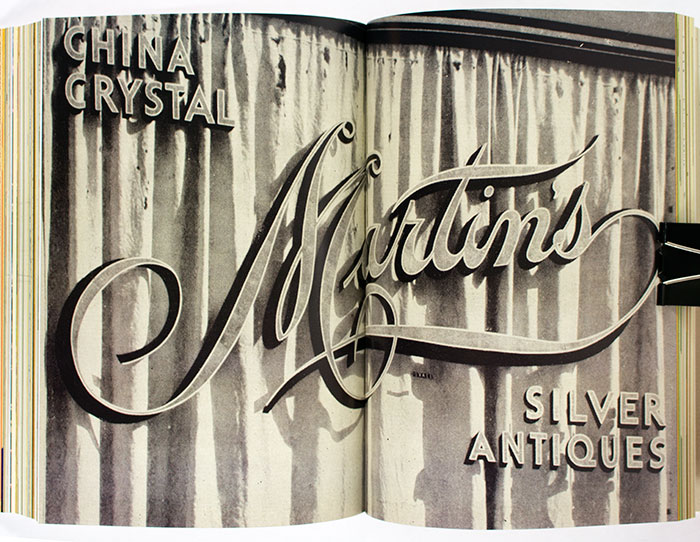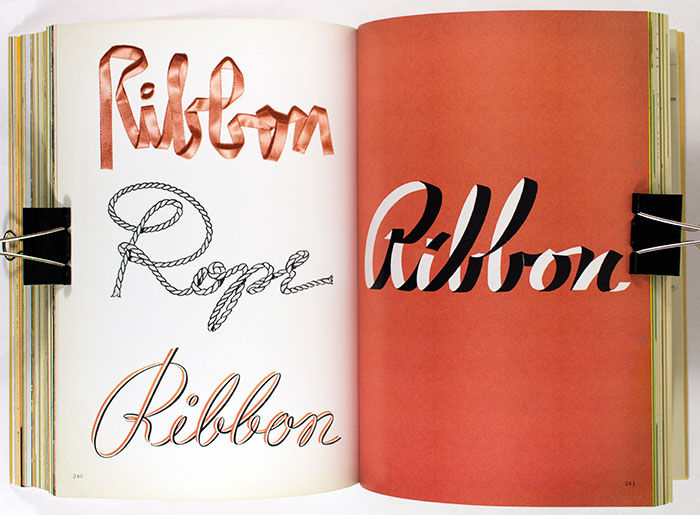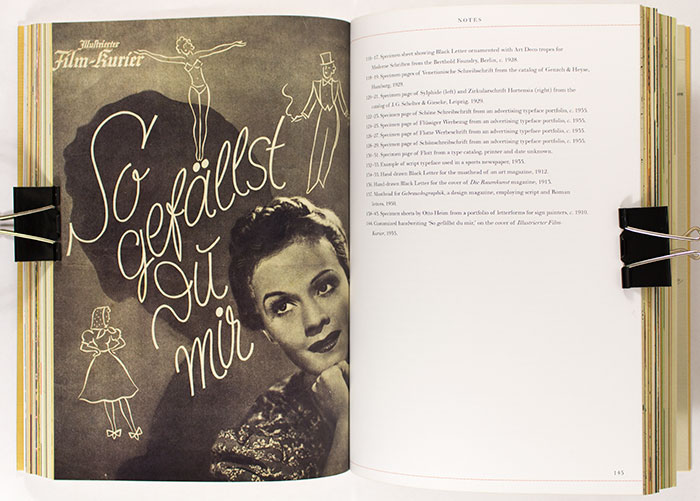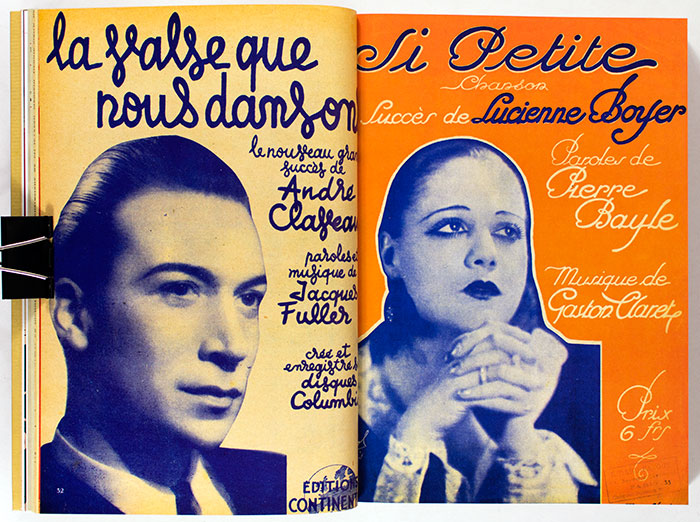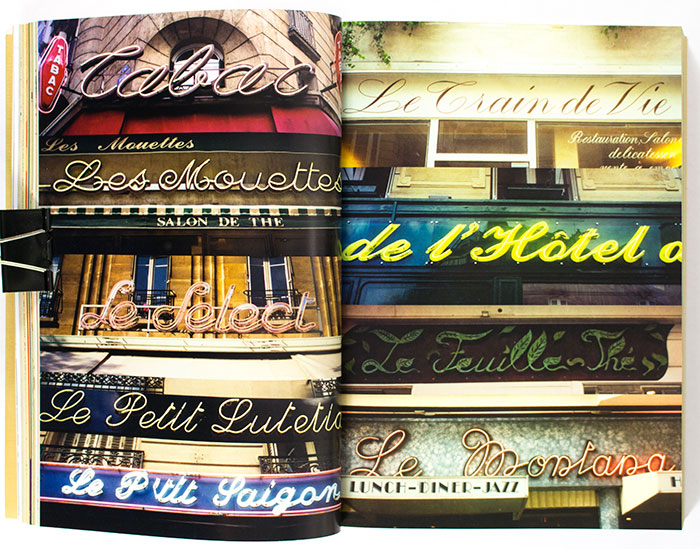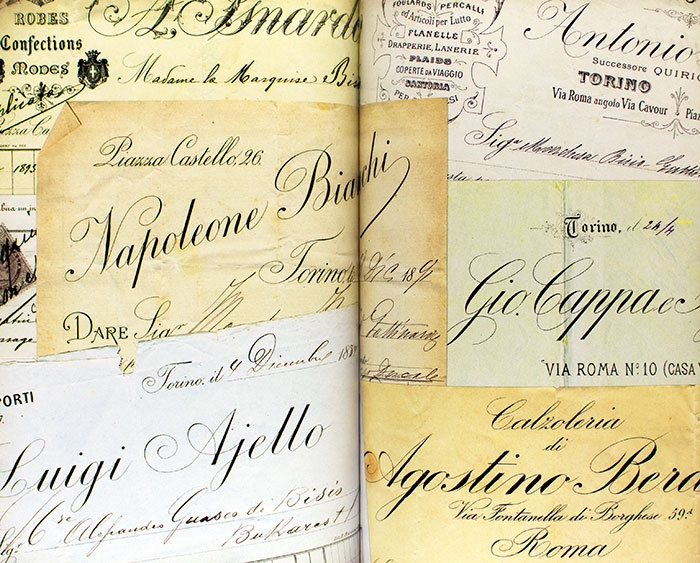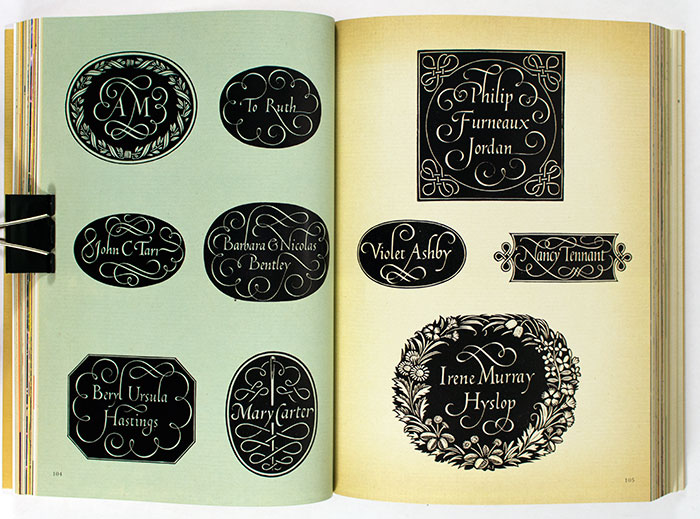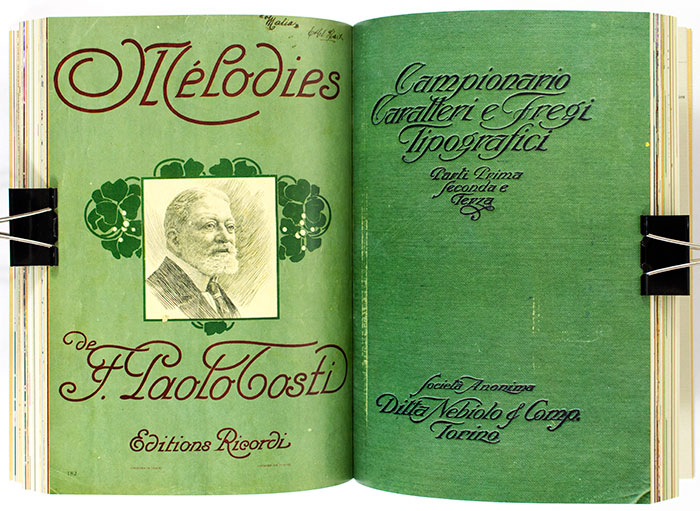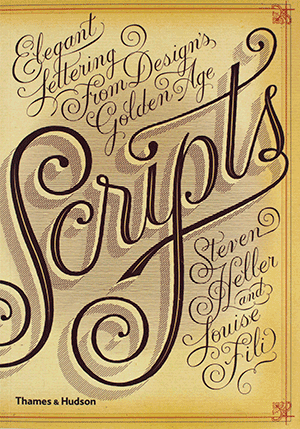
Scripts ist ein weiteres Sammelwerk von Steven Heller, in dem typografische Anwendungsbeispiele zu einem Thema zusammengetragen werden. Wie bei Shadow Type arbeitete Heller bei diesem Buch mit Luise Fili zusammen. In »Scripts« werden Schreibschriften und Schreibschriftenanwendungen von Anfang des 19. Jahrhunderts bis zur Mitte des 20. Jahrhunderts präsentiert. Die Zusammenstellung erfolgt nach den Land der Anwendung bzw. der Herkunft der Schriften: Großbritannien, Italien, Frankreich, Deutschland und USA. Zu jedem Land gibt es einen kurzen (englischen) Text, der die jeweiligen stilistischen Besonderheiten der Schreibschriften und ihrer Anwendung erklärt. Ansonsten ist das 352 Seiten starke Buch jedoch ein reines »Bilderbuch«, das vollformatig Schreibschrift ohne weitere Erklärungen oder Quellenangaben präsentiert. Die Auswahl ist recht vielfältig: Schriftmuster von Gießereien, Briefbögen, Logos, Poster, Anzeigen, Magazin- und Zeitungsseiten und Außenwerbung. Wer sich inspirieren lassen will und die historischen Stile und Anwendungen von lateinischen Schreibschriften in bestimmten Ländern anschauen möchte, findet in diesem Buch reichhaltiges Material.
Untertitel: Elegant Lettering from Design’s Golden Age
Autor(en): Steven Heller, Luise Fili